今回は、自分の「好きや愛」をまっすぐ伝えられる、日本語フリーフォントをご紹介します。
アイドルへの想い、趣味への情熱、大切なものへの愛着。そんな気持ちは、文字のトーンひとつでぐっと伝わり方が変わります。ポップな勢い、素直で飾らない丸文字など自分らしさをそのまま表現できるのが魅力です。
今回は、SNS投稿、メッセージカード、動画テロップなど、「好きや愛」を表現する場面にぴったりな日本語フリーフォントをピックアップしました。
“好きや愛”を文字で伝える。感情がにじむ日本語フリーフォントまとめ
以下の画像のように、「好きや愛を表現」する雰囲気にぴったりフォントをご紹介します。
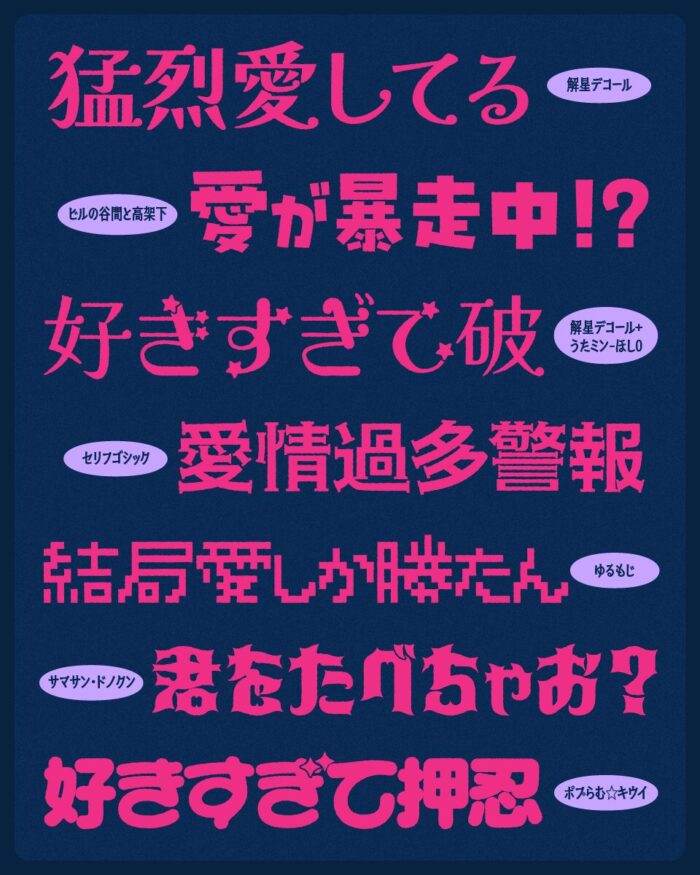
解星デコール
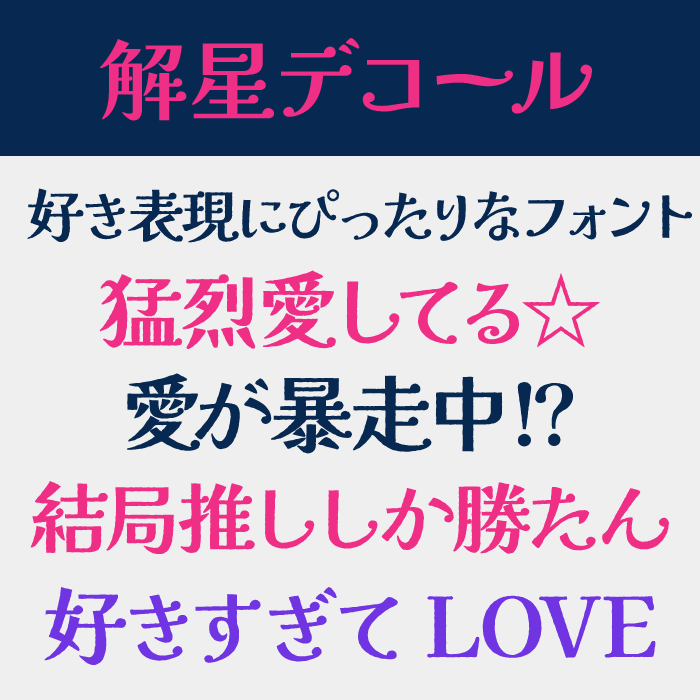
解星デコールは、装飾性とシャープさを併せ持つ、可愛らしいフォントです。音符のようなモチーフで、細部に遊びがあり、きらりとした個性が光ります。
「好きや愛を表現」を表現するのにぴったりなフォントです。
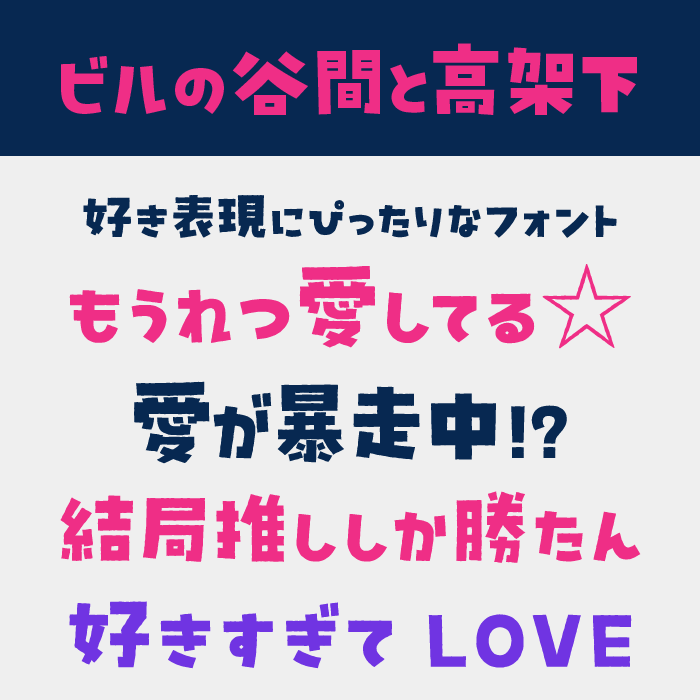
ビルの谷間と高架下は、デコボコ感のある個性的な字形が印象的なデザインフォントです。ストレートで飾らない線が、等身大の「好き」を伝えることができる可愛らしいフォントです。
うたミン・ほし0
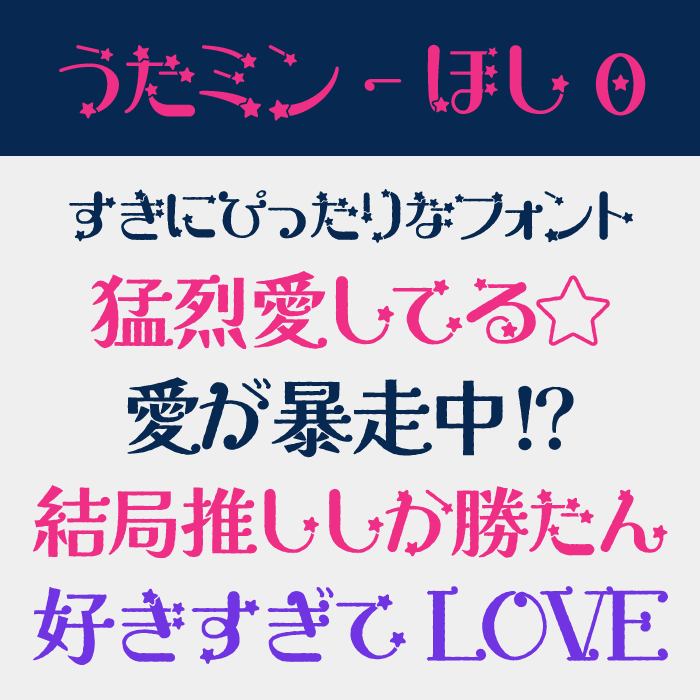
うたミン・ほし0は、星モチーフが散りばめられた、遊び心たっぷりのフォントです。
漢字が未収録なので、上記で紹介している解星デコールと組み合わせ使っても相性が良いです。
セリフゴシック
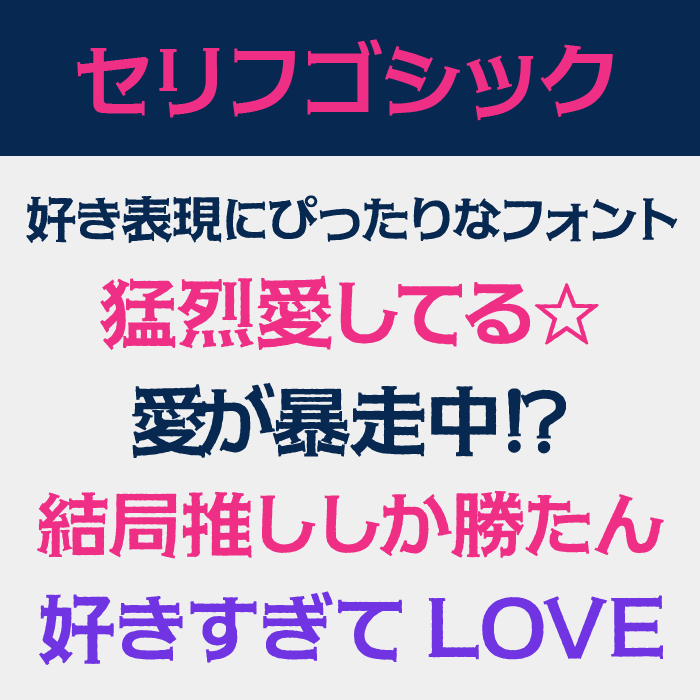
セリフゴシックは、ゴシック体の安定感にセリフのニュアンスを加えた個性的なフォントです。ほどよいクラシカルさがあり、大人っぽい「好き」を表現できます。
可愛さと知性のバランスを取りたいときにぴったりです。
ポプらむ☆キウイ
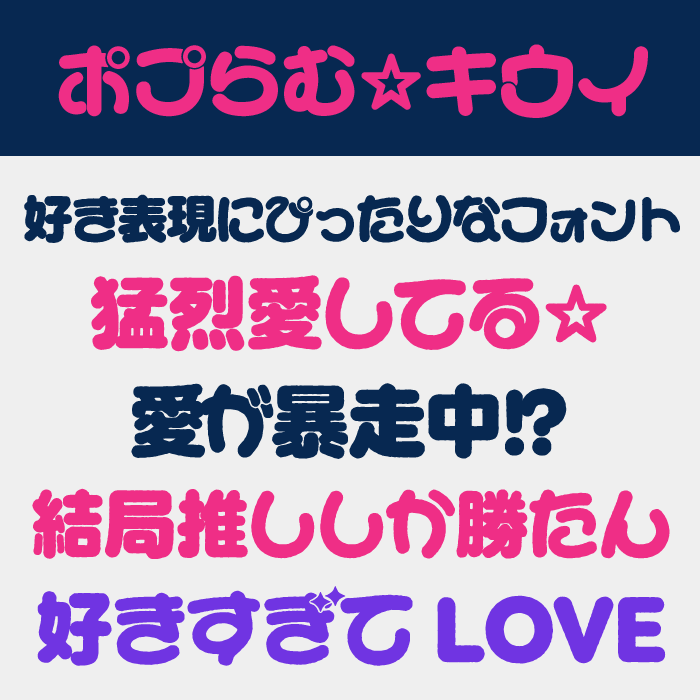
ふわらむ☆キウイは、キュートさに加えて少しポップな軽快さを持つフォントです。丸くて太めの線が、素直で無邪気な愛情や好きを伝えたいときにぴったりなフォントです。
ポプらむ☆キュート
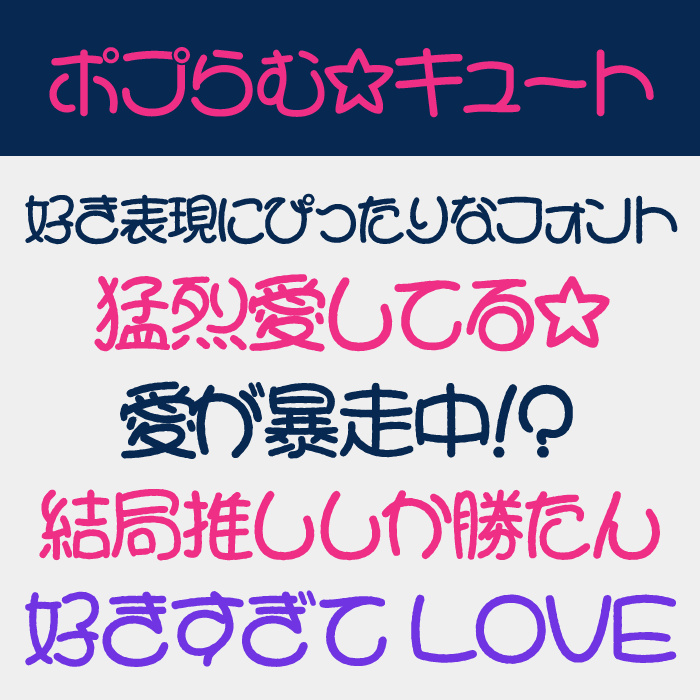
ふわらむ☆キュートは、丸文字で可愛らしくデコラティブな要素が特徴の、とびきり甘い雰囲気にぴったりなフォントです。ときめき感が高まるフォントです。
バナナスリップ
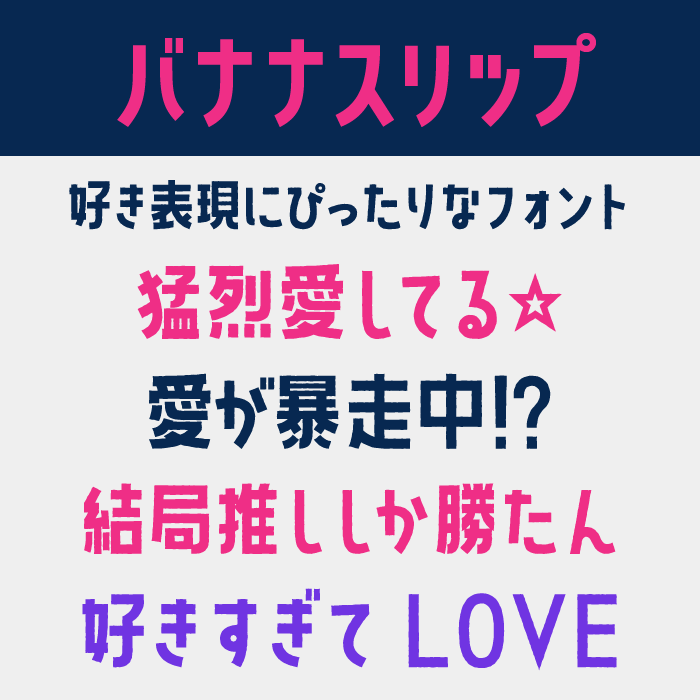
バナナスリップは、丸く太めの字形が印象的な、元気で勢いのあるフォントです。弾むようなシルエットが、テンション高めの「好き」をそのまま表現できるフォントです。
明るくポジティブな愛情表現と相性抜群です。
クラフト明朝
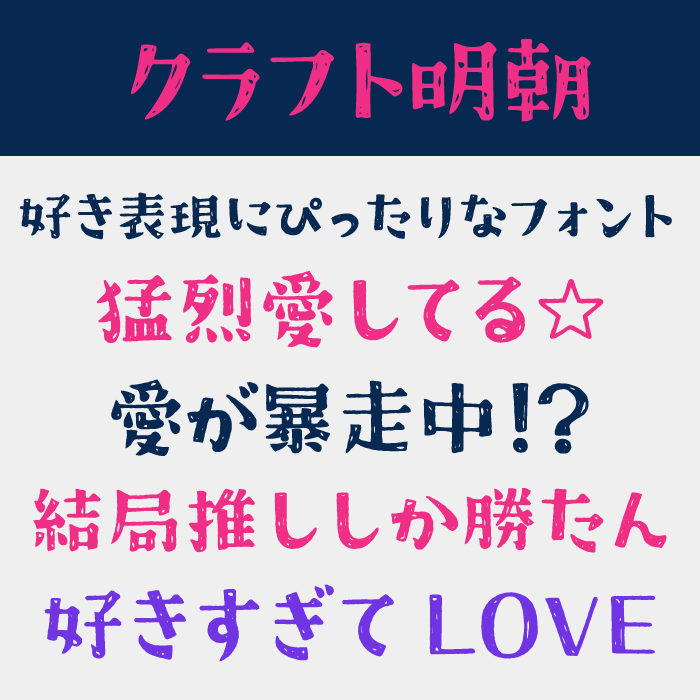
クラフト明朝は、ラフな質感と手作業のような手書きっぽさのある明朝体フォントです。少しざらついた線が、熱量のある「大好き」を視覚的に表現します。
和音Joyo
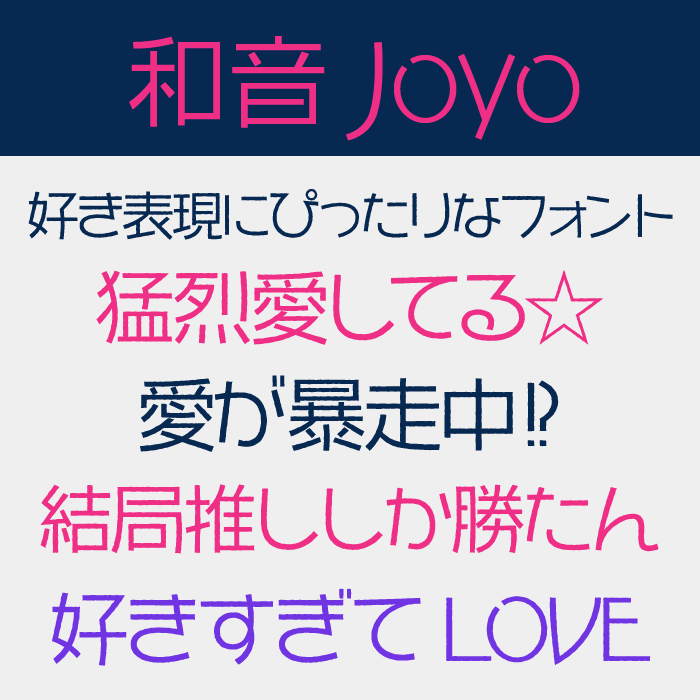
和音Joyoは、すっきりと整った骨格にほんのり丸みを感じる、バランスの良いフォントです。可読性を保ちながらも親しみやすさがあり、まっすぐな愛情表現に向いています。
なぎの
なぎのは、丸みのある線とゆるやかなリズムが心地よい、やさしい印象のフォントです。角を立てない字形が、素直な「好き」という気持ちをそのまま言葉にしたような空気をまとっています。
サマサン・ドノクン
サマサン・ドノクンフォントは、ゴシック調で「ダークでカッコいい雰囲気」をもつデザインフォントです。強がっているけど甘えたい、そんな好きを表現するのにぴったりなフォントです。